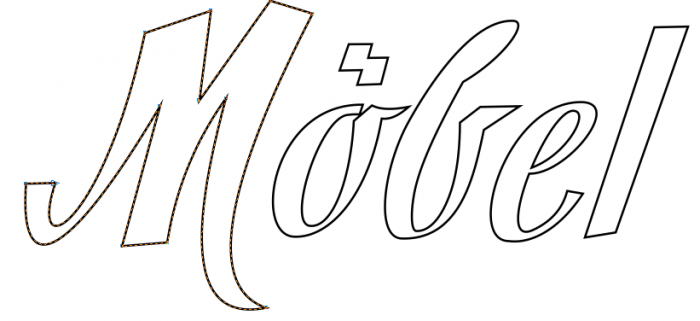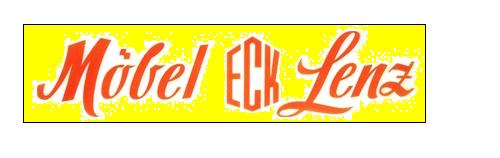
Schrift gesucht (Möbel-Eck)
Ich habe folgendes Problem: Ein Logo, was nachgebaut werden soll, aber Schrift(en) konnte(n) weder genannt noch geliefert werden :(. Vielleicht könnt Ihr mir ja helfen :).
Ich denke, das "Eck" kann man evtl so nachbauen, aber die Schreibschrift ... Hmmmm
Den Rest kann man auch direkt so nachzeichnen ...
Vor allem weil es wohl eh gezeichnet und keine Satzschrift ist  :tuschel:
Ansonsten guck dir mal die Zierfische oder diese Liste an ...
also ich persönlich bin da nicht wirklich versiert drin und hocke auch schon stundenlang dran :(. da investier ich mehr, als am ende bei rumkommt
Also, ich schätze mal, länger als eine halbe Stunde würde ich daran nicht zeichnen... Das ist mit einer Vektorgrafik doch wirklich kein Probvlen, es sei denn, auch dieses gelbe drum herum gehört zum Logo, aber da hülfe die Schrift ja auch nicht.
12 Minuten, nur mal zum Test: